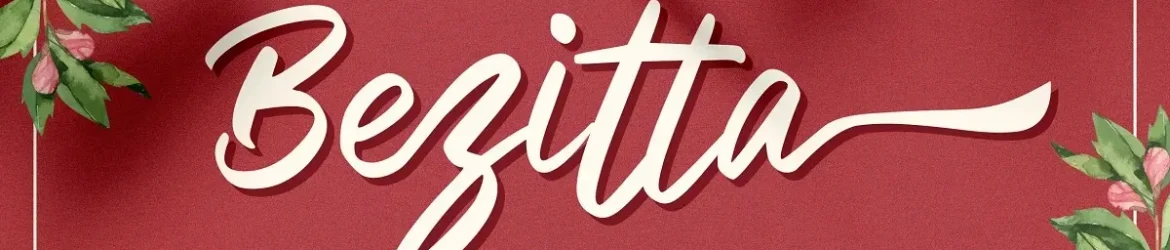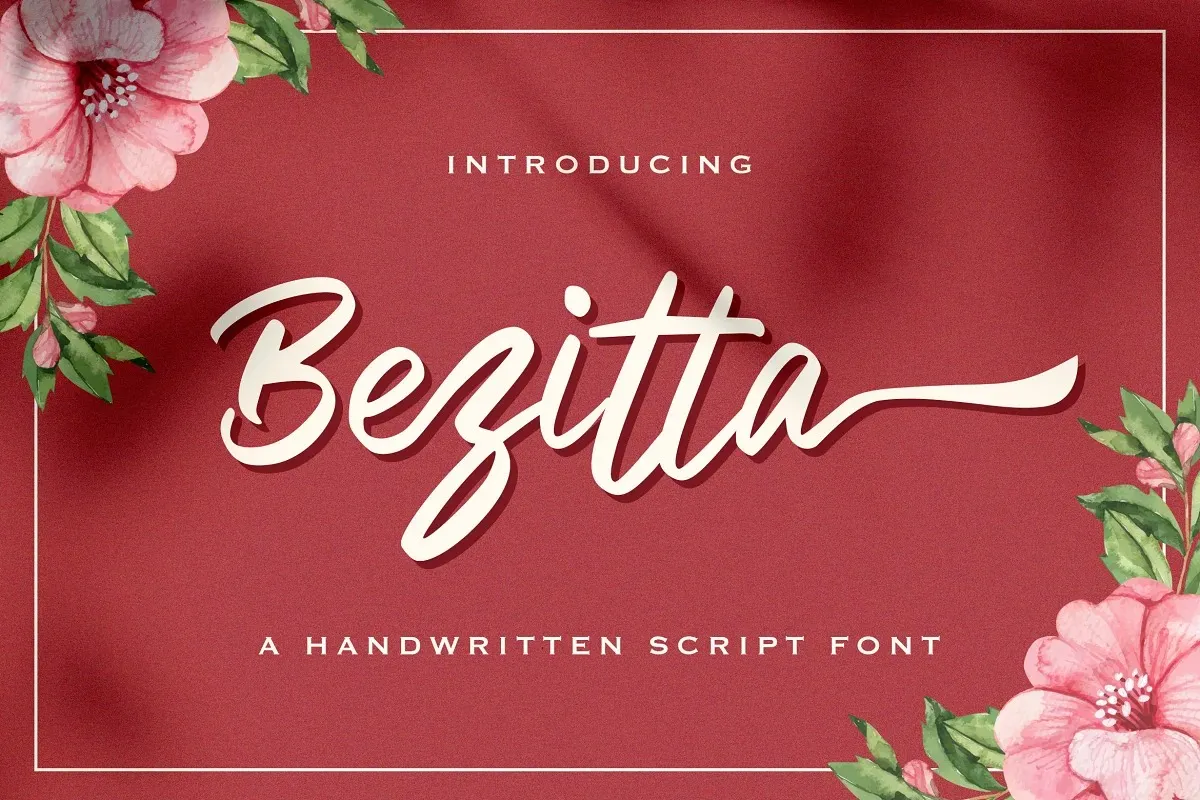
Bezitta Font – Fonte Grátis
Bezitta Font
A fonte ‘Bezitta Font’ é uma opção única para quem busca um estilo elegante com um toque descontraído. Fabricada pela StringLabs, esta fonte script apresenta um visual de escrita à mão que se torna instantaneamente apelativo. O design suave e casuais dá ao texto uma aparência despojada e autêntica, enquanto o pequeno “bounce” no final das linhas adiciona um toque de vida aos caracteres. Essa fonte apresenta uma combinação perfeita de beleza e equilíbrio entre os caracteres, tornando-a excelente para diversas aplicações gráficas, desde design editorial até criações digitais. Com seu estilo casual mas elegante, ‘Bezitta Font’ é um recurso valioso para quem busca fazer seus projetos realmente brilhar. Engane-se: esta font pode transformar suas ideias mais criativas em realidade.